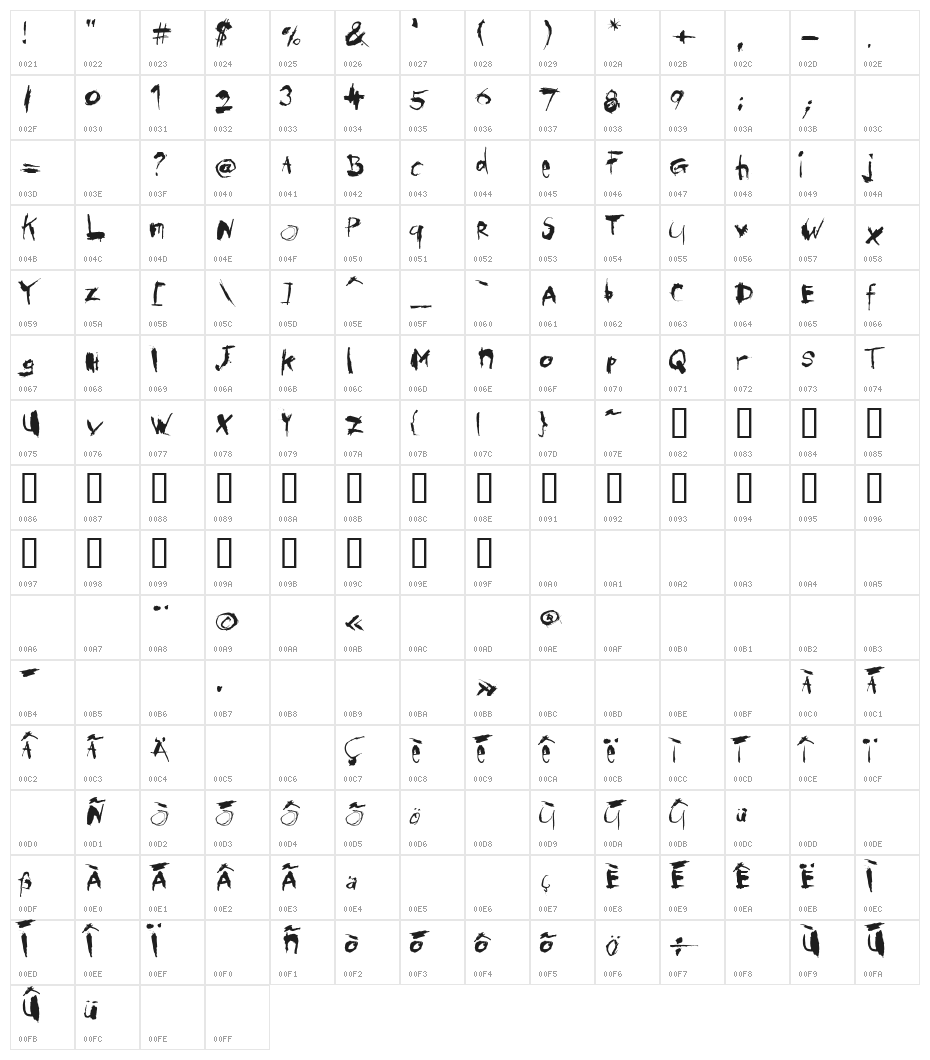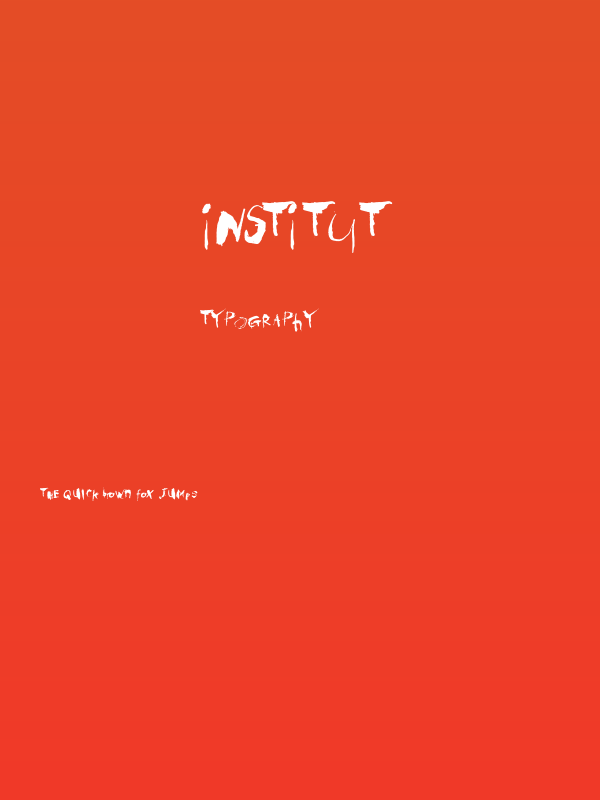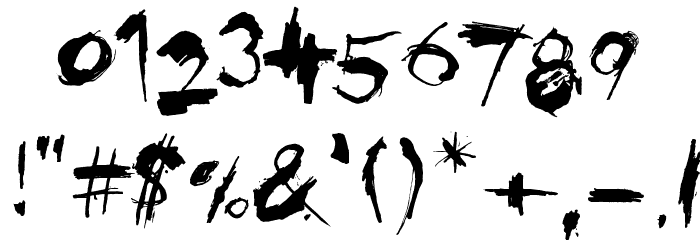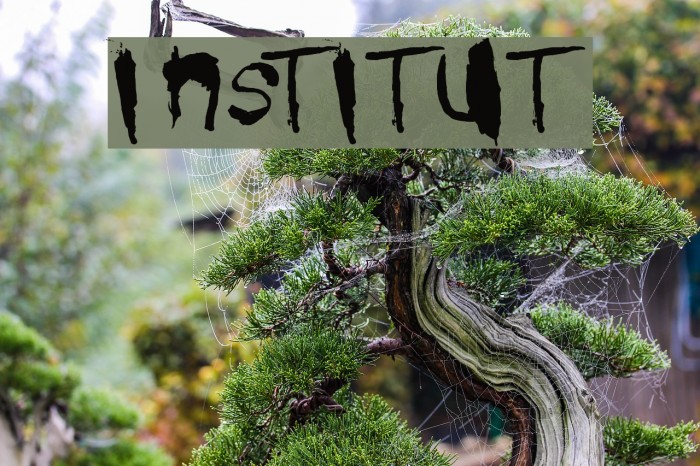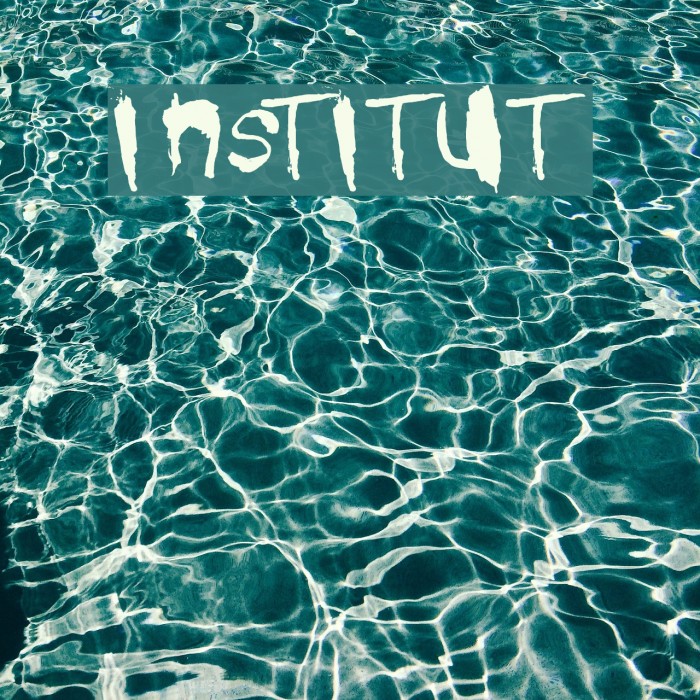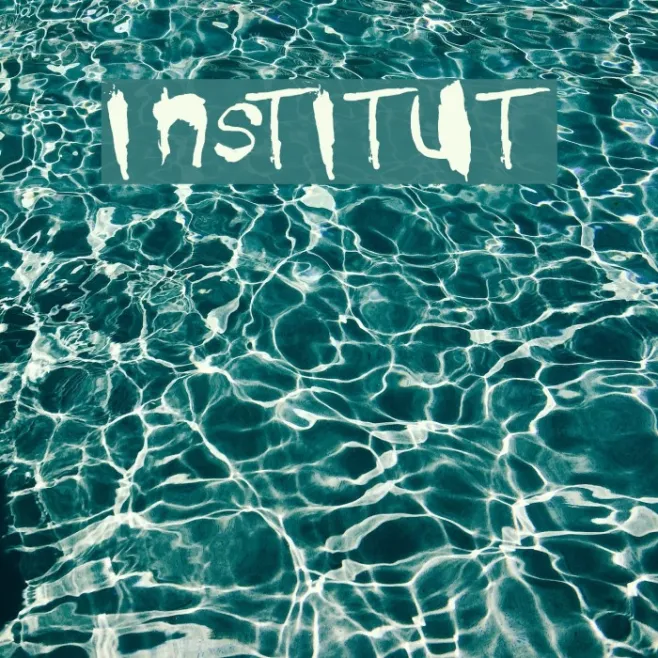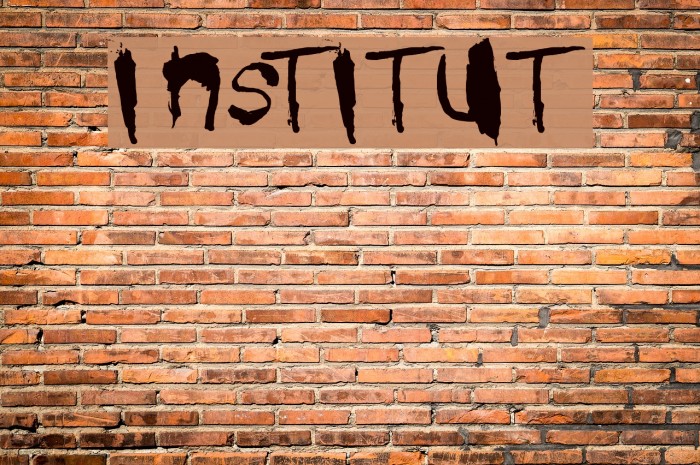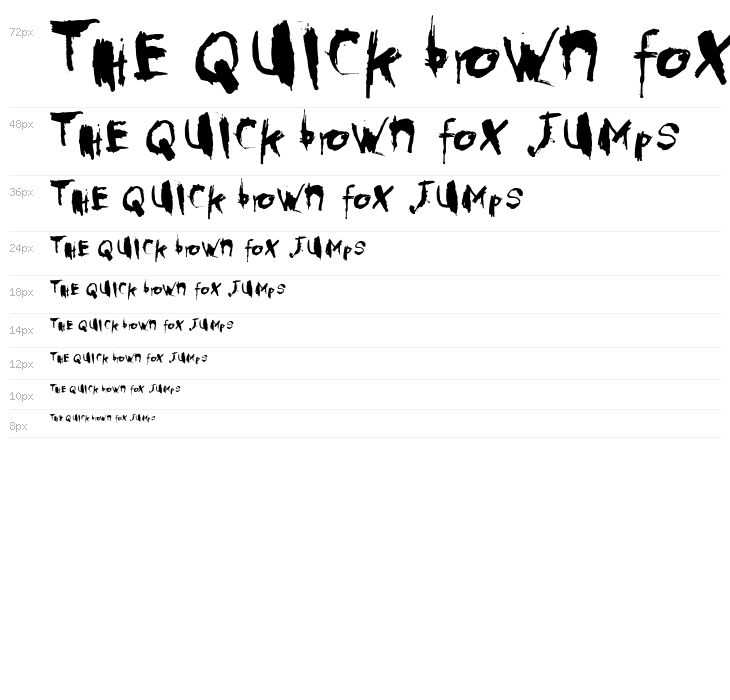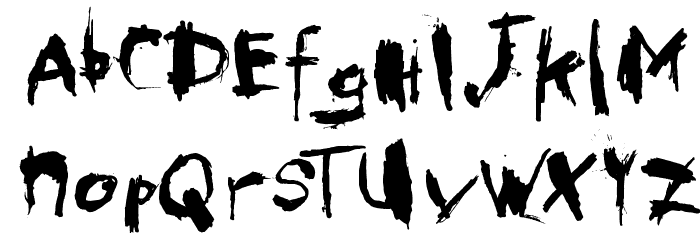
institut Font
| Categorías | Thick |
| Proyectos propuestos | Ideal for album covers, street art-inspired designs, posters, and edgy branding projects. |